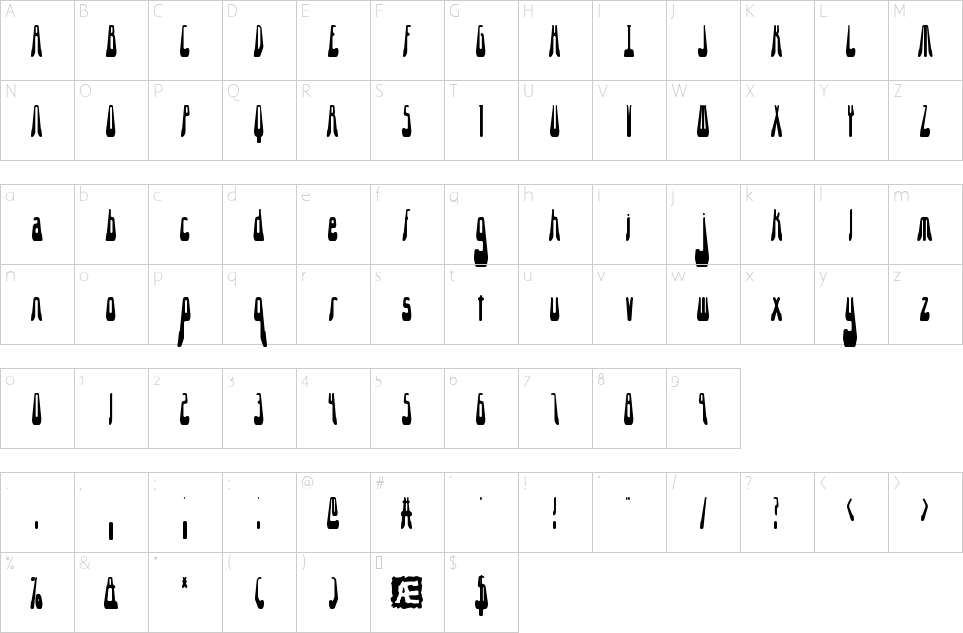
1015 Saturday Night Font – Download Grátis
Aqui está uma descrição envolvente para a página de download da fonte 1015 Saturday Night Font: Através do site Aenigma Fonts, encontramos uma fonte notável que merece sua atenção: 1015 Saturday Night. Esta elegante e minimalista fonte foi especialmente projetada para aqueles que buscam um equilíbrio perfeito entre modernidade e sofisticação. Seu design cuidadoso torna-a ideal tanto para o uso em sites como em aplicativos de escritório, garantindo uma experiência de leitura agradável em qualquer plataforma — seja Windows ou Mac. Com seu design original e versátil, 1015 Saturday Night é perfeita para criar textos estilizados, gráficos impactantes ou até mesmo para personalizar mensagens de texto. Se você busca uma fonte única que vai diferenciá-lo dos demais, esta fonte certamente o atenderá. Aenigma Fonts fez um trabalho incrível ao lançar 1015 Saturday Night e estamos ansiosos para ver como ela irá se adaptar em seu projeto. Essa é uma oportunidade de adquirir semelhante a uma obra de arte, pois 1015 Saturday Night não apenas oferece um aspecto visual atraente, mas também a flexibilidade necessária para qualquer projeto. Descubra agora como 1015 Saturday Night pode transformar seu design em algo único e memorável.